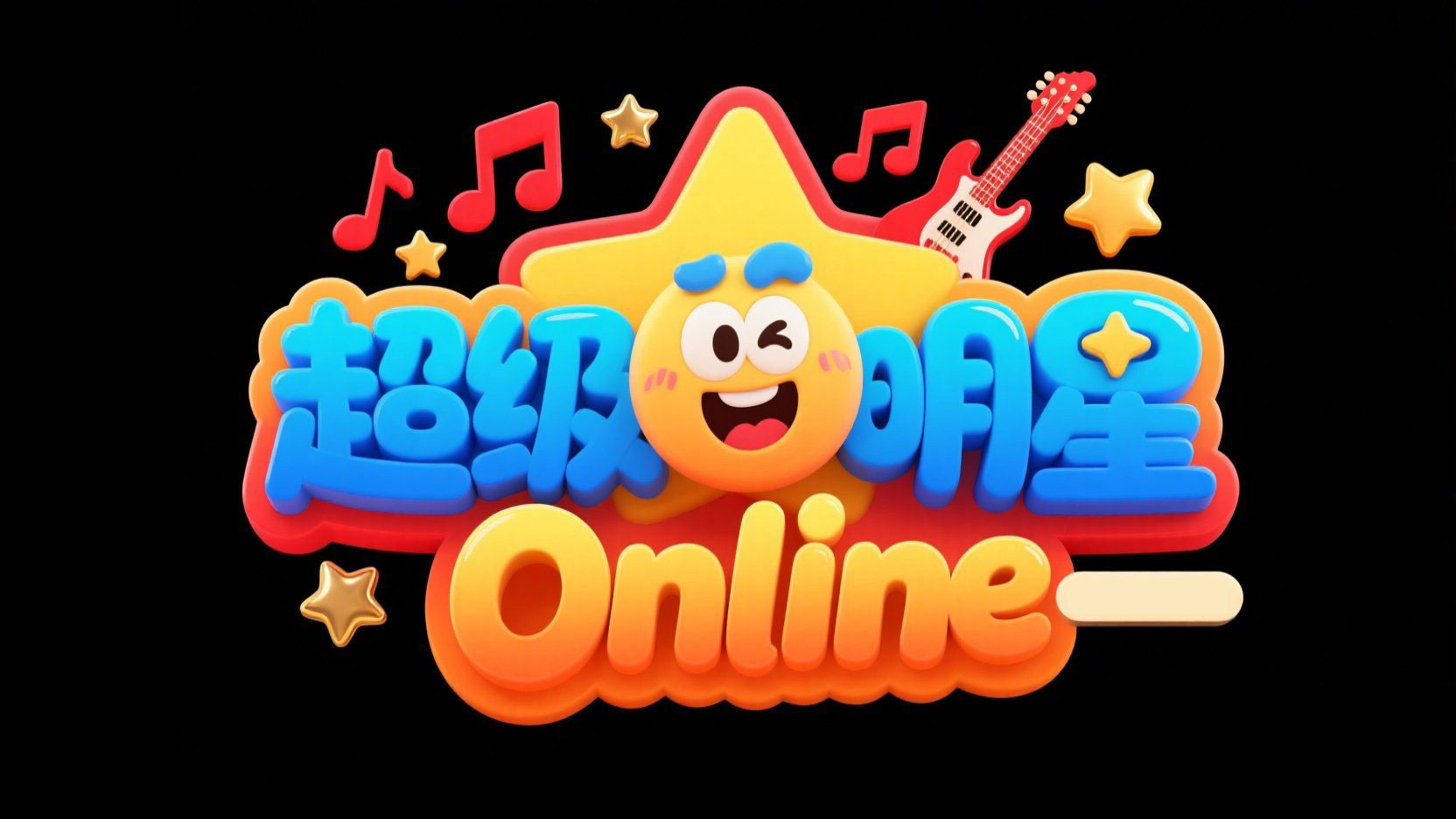
创作 “超级明星 Online” 标题,用圆润流畅、活泼...
创作 “超级明星 Online” 标题,用圆润流畅、活泼...AI字体提示词
风格定位
适合做风格探索与字形灵感延展。
适合场景
海报设计、品牌标题、电商设计、创意视觉
创作 “超级明星 Online” 标题,用圆润流畅、活泼俏皮的卡通艺术字体;以高饱和蓝黄橙渐变为主色,搭配红吉他、金星星、音符装饰;添加深色细轮廓边框,呈现光滑矢量卡通质感;融入吉他、音符、星星及网址元素,营造绚丽活力的娱乐明星氛围 。背景为干净的黑色。
生成建议
• 先保留核心风格词,再替换材质、颜色和光影词做多轮尝试。
• 如果用于品牌标题字,补充品牌气质、行业属性和情绪关键词。
• 如果用于海报或电商标题,额外强调大字、对比度和视觉冲击力。